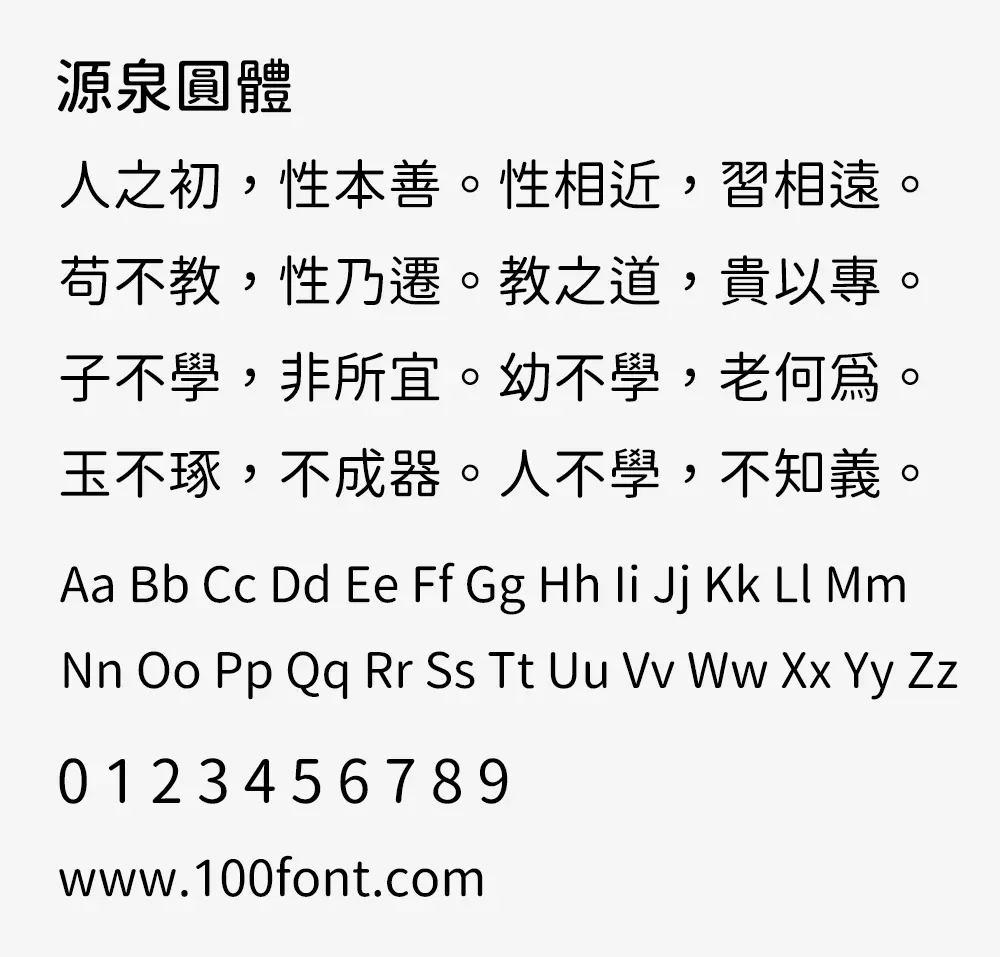
源泉圓體是基於思源黑體的開放原始碼中文字體,彌補一直沒有正統圓體開源字體的缺憾。黑體的開源字體非常多,但一直缺乏正統圓體的開源字體。像源柔ゴシック之類的字體都留有黑體的腳,乍看的感覺還是很黑體。
本字體不只把筆畫全改圓,也將黑體的腳儘可能拔除,並加上封閉區域的內圓角處理,儘可能去逼近圓體樣貌。
免責事項:本字體乃以計算機程序自動進行改造,如上述拔腳的作業充滿猜測性。部分文字可能有腳沒拔掉,部分文字可能正常的筆畫被誤判是腳而誤拔。由於此為興趣性的開源字體項目,雖已試圖強化猜測算法減少誤判,但仍無法保證沒有錯誤。在正式場合使用時請自行確認文字正確性。基本上較細的字重效果會較好且較正確,而愈粗的字重錯誤會較多。
注意提醒:這款字體主要適用於繁體,雖然簡體中文也支持一部分,但是簡體容易出現錯別字。